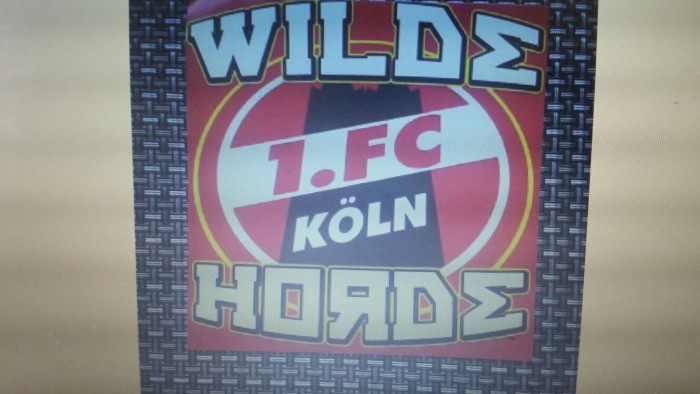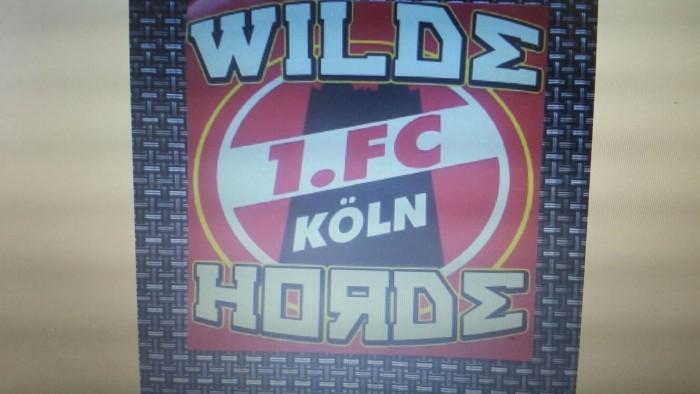
Suche Font (Wilde Horde)
Ich suche die Schriftart von "WILDE HORDE".
Ich hatte schon überlegt, ob das E vllt ein gekipptes M ist.
Kennt wer die Schrift?
Jetzt ist die Schwierigkeit, eine Schriftart zu finden, die sowohl das Σ als auch das Я beinhaltet und dazu noch dieses gekantete "D" hat.
Stimmt!
Darf ich frage, wie du sie gefunden hast?
Oder kanntest du die schon?
Nun, bei allem, was sich um Freefonts dreht, ist Dafont.com eigentlich immer die beste Seite. Der Betreiber macht da nbämlich einen guten Job, indem er die Schriften nicht nur alfabetisch einsortiert, sondern diese versucht thematisch einzusortieren. Und da diese Schrift eben mit den missbrauchten Buchstaben aus kyrillischer und griechischer Schrift daher kommt, ist e da eben der beste Weg, bei den Pseudo-Fremdländischen zu suchen.
eine weitere seriöse und ähnlich gut sortierte Seite ist 1001freefonts.com
Darf ich frage, wie du sie gefunden hast?
Nun vor ein paar Jahren hatte ich ein Freefont-Paket aus dem Netz geladen in welchem die Schriften thematisch sortiert waren z.B. Feuer, Eis, Liebe, Weihnachten usw. Eine Unterkategorie war auch Pseudo-Fremdsprachen welche dann nochmal nach Ländern aufgeschlüsselt war. In diesem Paket fand ich auch jene Schrift.
Ohne diesen „Heimvorteil“ hätte ich aber, wie Catfont empfohlen, die Dafont-Themenseite bemüht. Auch auf Myfont.de (nicht zu verwechseln mit Myfonts) gibt es eine solche Themenseite.
Dafont habe ich auch "gründlich" durchforstet, allerdings bin ich nicht auf die Idee gekommen, dass die gesuchte Schriftart unter "Russisch" zu finden ist.
Ich habe dafür die kompletten 18 Seiten bei Basic-Serifs durchsucht - mehrmals.
Dabei hätte es so einfach sein können - mit dem richtigen Ansatz zumindest.